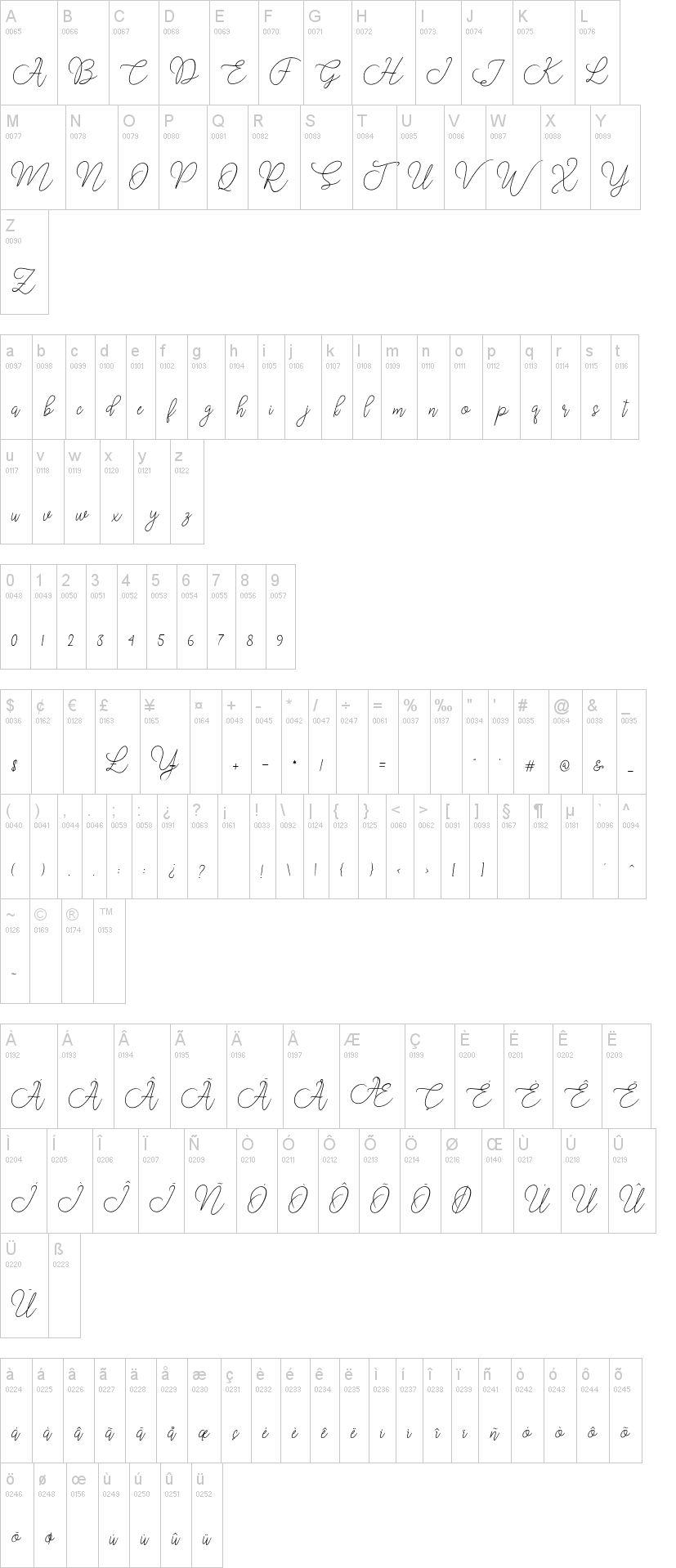
Moon Chin 字体是由南韩设计师 Moon Chin 创作的一款漂亮的非常有趣的字体。字体灵感来自于月亮,圆润的线条给人一种柔和的感觉。字体的特点是它的节奏感和柔和的线条,是一种非常有趣的折衷字体,既有传统楷体的稳重,又有现代字体的时尚感。Moon Chin 字体可以用于各种应用,包括网站、平面设计、标志设计和印刷等。内容介绍
Moon Chin是一款非常不错的手写艺术字体,具有很好的视觉感,适合于文化类的宣传设计、商业类品牌的广告和产品包装设计以及个性化文字排版等较多场景。